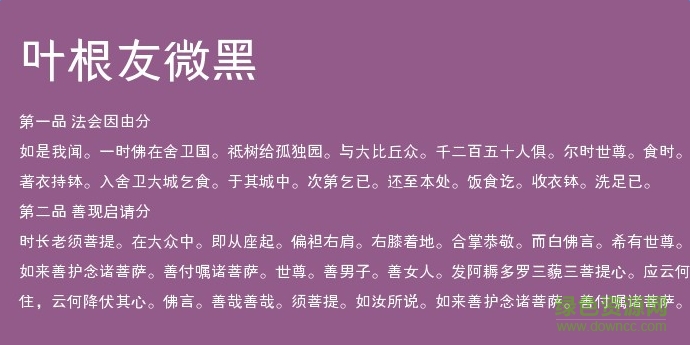
葉根友微黑簡(jiǎn)
葉根友微黑簡(jiǎn)體是一款古典正規(guī)風(fēng)格字體軟件,微黑簡(jiǎn)體筆畫工整非常鮮明醒目,字體所占空間非常一致,藝術(shù)氣息十足,在海報(bào)廣告標(biāo)題有著不小的應(yīng)用,還有更多好看字體歡迎來(lái)綠色資源網(wǎng)下載體驗(yàn)!
葉根友微黑簡(jiǎn)體是一款正規(guī)的黑體類型的印刷體,整個(gè)字體輕松活潑而有時(shí)代鮮明的特征,整個(gè)筆畫橫度微斜切,干凈而大氣,簡(jiǎn)約是這款字體的主要特色。每個(gè)筆畫15度斜角的設(shè)計(jì),使整個(gè)字型看起來(lái)更具時(shí)尚大氣,在應(yīng)用于內(nèi)文、標(biāo)題等都是不錯(cuò)的選擇,葉根友微黑從設(shè)計(jì)到制作歷時(shí)數(shù)年,工程量是普通手寫字體的數(shù)倍,每個(gè)筆畫和結(jié)構(gòu)架次都需要經(jīng)過(guò)精心布局,以求好的效果呈現(xiàn)給用戶。
葉根友微黑簡(jiǎn)體
該字體筆畫工整,一筆一畫毫不拖泥帶水,在一些正式文章的書寫印刷方面得到廣泛的應(yīng)用,整體效果十分優(yōu)美耐看,值得使用收藏!